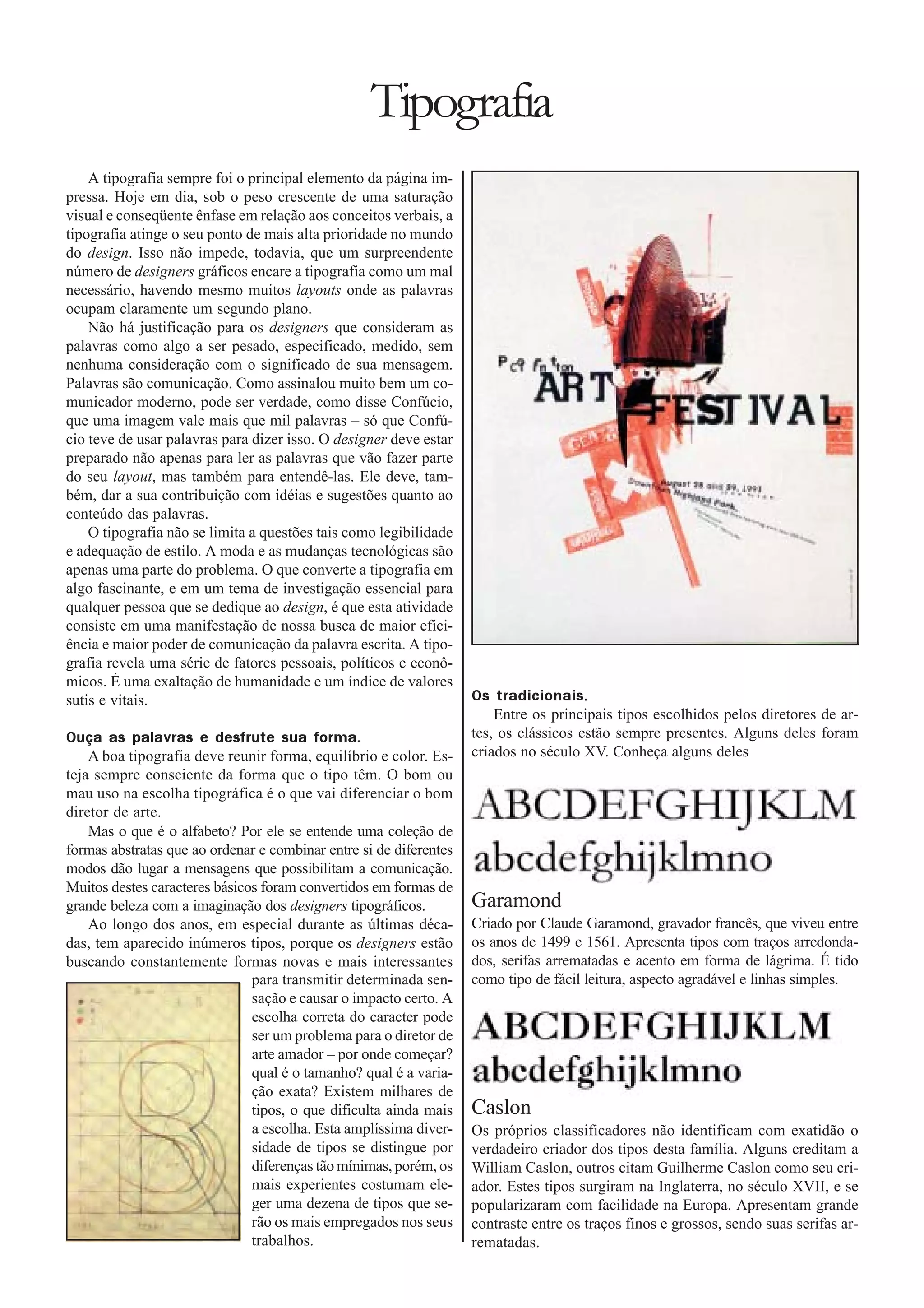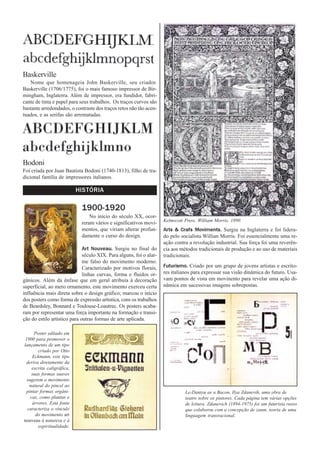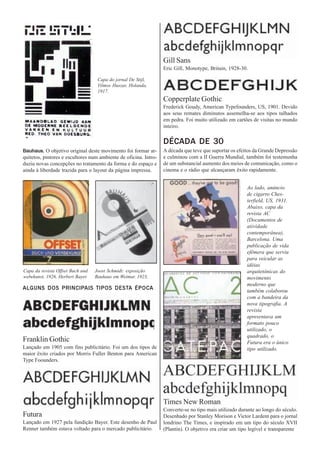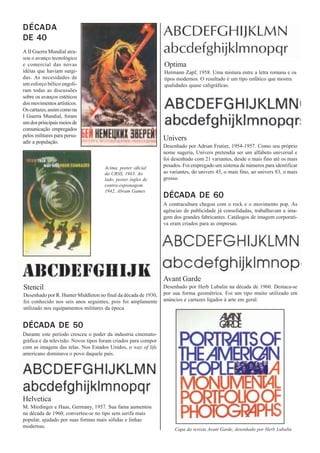
Tipografia
A tipografia sempre foi o principal elemento da página im-
pressa. Hoje em dia, sob o peso crescente de uma saturação
visual e conseqüente ênfase em relação aos conceitos verbais, a
tipografia atinge o seu ponto de mais alta prioridade no mundo
do design. Isso não impede, todavia, que um surpreendente
número de designers gráficos encare a tipografia como um mal
necessário, havendo mesmo muitos layouts onde as palavras
ocupam claramente um segundo plano.
Não há justificação para os designers que consideram as
palavras como algo a ser pesado, especificado, medido, sem
nenhuma consideração com o significado de sua mensagem.
Palavras são comunicação. Como assinalou muito bem um co-
municador moderno, pode ser verdade, como disse Confúcio,
que uma imagem vale mais que mil palavras – só que Confú-
cio teve de usar palavras para dizer isso. O designer deve estar
preparado não apenas para ler as palavras que vão fazer parte
do seu layout, mas também para entendê-las. Ele deve, tam-
bém, dar a sua contribuição com idéias e sugestões quanto ao
conteúdo das palavras.
O tipografia não se limita a questões tais como legibilidade
e adequação de estilo. A moda e as mudanças tecnológicas são
apenas uma parte do problema. O que converte a tipografia em
algo fascinante, e em um tema de investigação essencial para
qualquer pessoa que se dedique ao design, é que esta atividade
consiste em uma manifestação de nossa busca de maior efici-
ência e maior poder de comunicação da palavra escrita. A tipo-
grafia revela uma série de fatores pessoais, políticos e econô-
micos. É uma exaltação de humanidade e um índice de valores
sutis e vitais.                                                     Os tradicionais.
Entre os principais tipos escolhidos pelos diretores de ar-
Ouça as palavras e desfrute sua forma.                              tes, os clássicos estão sempre presentes. Alguns deles foram
A boa tipografia deve reunir forma, equilíbrio e color. Es-     criados no século XV. Conheça alguns deles
teja sempre consciente da forma que o tipo têm. O bom ou
mau uso na escolha tipográfica é o que vai diferenciar o bom
diretor de arte.
Mas o que é o alfabeto? Por ele se entende uma coleção de
formas abstratas que ao ordenar e combinar entre si de diferentes
modos dão lugar a mensagens que possibilitam a comunicação.
Muitos destes caracteres básicos foram convertidos em formas de
grande beleza com a imaginação dos designers tipográficos.          Garamond
Ao longo dos anos, em especial durante as últimas déca-         Criado por Claude Garamond, gravador francês, que viveu entre
das, tem aparecido inúmeros tipos, porque os designers estão        os anos de 1499 e 1561. Apresenta tipos com traços arredonda-
buscando constantemente formas novas e mais interessantes           dos, serifas arrematadas e acento em forma de lágrima. É tido
para transmitir determinada sen-     como tipo de fácil leitura, aspecto agradável e linhas simples.
sação e causar o impacto certo. A
escolha correta do caracter pode
ser um problema para o diretor de
arte amador – por onde começar?
qual é o tamanho? qual é a varia-
ção exata? Existem milhares de
tipos, o que dificulta ainda mais    Caslon
a escolha. Esta amplíssima diver-    Os próprios classificadores não identificam com exatidão o
sidade de tipos se distingue por     verdadeiro criador dos tipos desta família. Alguns creditam a
diferenças tão mínimas, porém, os    William Caslon, outros citam Guilherme Caslon como seu cri-
mais experientes costumam ele-       ador. Estes tipos surgiram na Inglaterra, no século XVII, e se
ger uma dezena de tipos que se-      popularizaram com facilidade na Europa. Apresentam grande
rão os mais empregados nos seus      contraste entre os traços finos e grossos, sendo suas serifas ar-
trabalhos.                           rematadas.
Baskerville
Nome que homenageia John Baskerville, seu criador.
Baskerville (1706/1775), foi o mais famoso impressor de Bir-
mingham, Inglaterra. Além de impressor, era fundidor, fabri-
cante de tinta e papel para seus trabalhos. Os traços curvos são
bastante arredondados, o contraste dos traços retos não tão acen-
tuados, e as serifas são arrematadas.
Bodoni
Foi criada por Juan Bautista Bodoni (1740-1813), filho de tra-
dicional família de impressores italianos.
HISTÓRIA
1900-1920
No início do século XX, ocor-
Kelmscott Press, William Morris, 1890.
reram vários e significativos movi-
mentos, que viriam alterar profun-      Arts & Crafs Moviments. Surgiu na Inglaterra e foi lidera-
damente o curso do design.              do pelo socialista Willian Morris. Foi essencialmente uma re-
ação contra a revolução industrial. Sua força foi uma reverên-
Uma família detipos pode apresentar todas as variações abaixo, mas você pode encontrar famílias de tipos com variações menores. Corpo Entrelinhas É o que determina o tamanho da letra. Esta medida Espaço entre as linhas se refere a distância entre a face anterior e posterior do tipo. Espelho Esboço das páginas de um jornal. Linotipo Máquina de compor, inventada por Ottmar Mergenthaler. Tem esse nome porque o jornalista norte-americano Whithelaw Reid, ao ver a máquina em funcionamento pela primeira vez, tomou a composição produzida e exlcamo: “A line of type”. A composição é feita com chumbo derretido e depois é reaproveitada. Entreletras Espaço entre as letras Medidas tipográficas Antigamente, para compor o texto era utilizado Entrelinhas duas medias tipográficas para determinar a largura Espaço entre as linhas do texto: Cícero - baseadas no Ponto Didot, que tem, Capitular aproximadamente, 0,3759 milímetros. 1 cícero tem 12 pontos = 4,5108 minlímetros Letra usada na abertura das composições, de Pica - sitema norte-americano que corresponde a tamanho maior que os tipos do texto. cerca da sexta-parte da polegada (4,218 milímetros) 1 cícero tem 12 pontos. Clichê Chapa de impressão usado na impressão pelo método da tipografia. Pouco utilizado atualmente. O método atual é o offset Bibliografia. Lewis Blackwell, Tipografia del siglo XX, Editorial Bustavo Gili, SA, Barcelona; Alain Weill, The Poster - A Worldwide Surey and History, Sotheby’s Publications, New York; Liz McQuiston e Barry Kitts, Graphic Design - Source Book, Macdonald Orbis, London; Michael Beaumont, Tipo & Color, Hermann Blume, Madrid; Jornal O Estado de S. Paulo, Tipologia do Caos. James Graig, Produção Gráfica. Editora Mosaico.